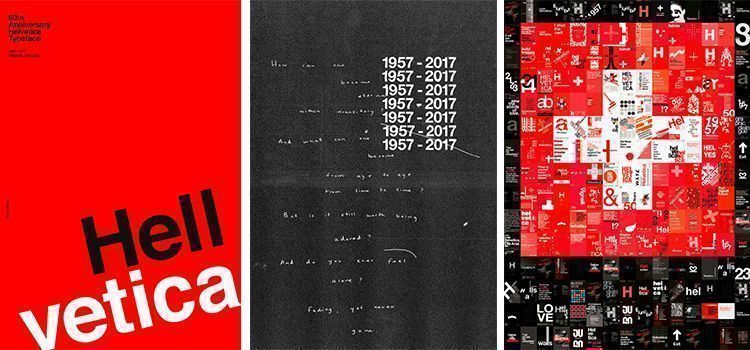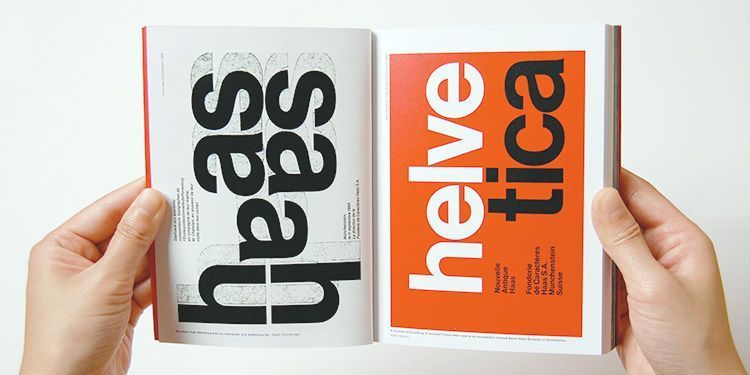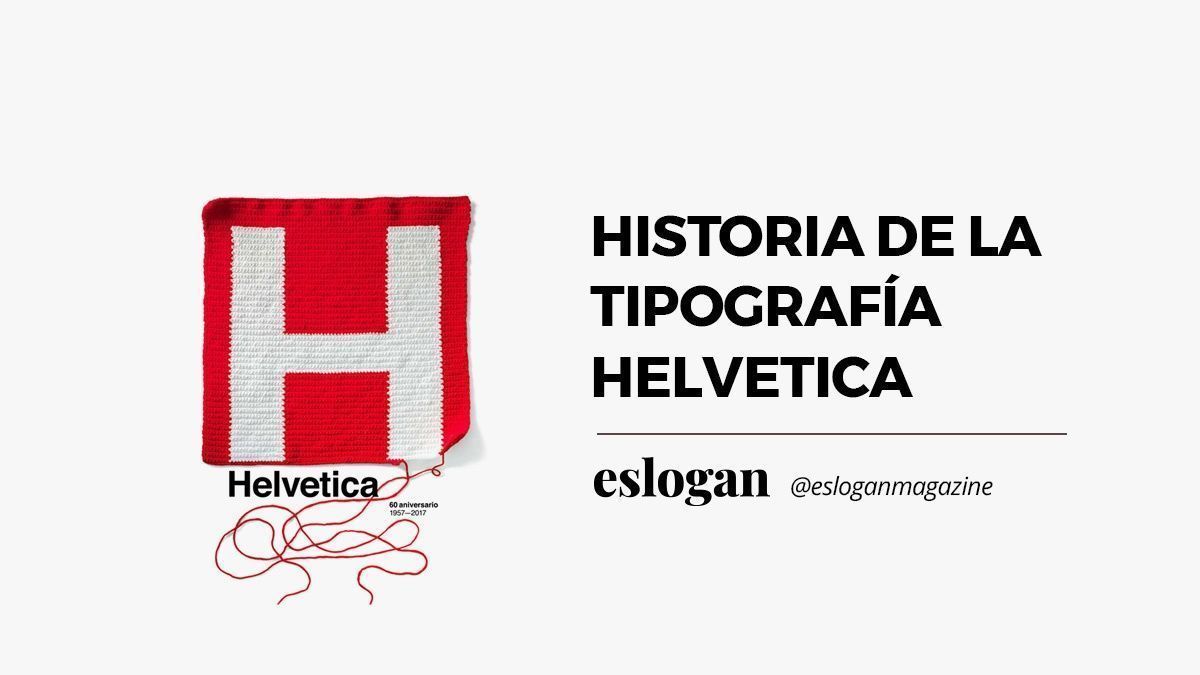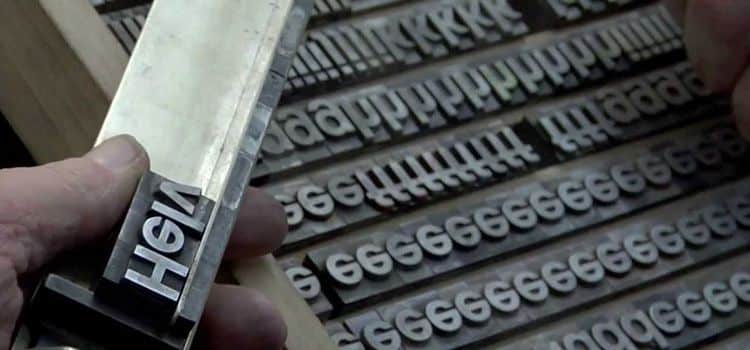
Historia de la tipografía Helvetica
Historia Tipografía Helvetica
La popular tipografía Helvetica cumple 60 años. Repasamos su historia, creación y aplicación.
La tipografía Helvetica cumple 60 años. La que podríamos definir como una de las tipografías legendarias, máxima expresión del estilo suizo que trajo la modernidad en el diseño a mediados del siglo XX y cuya influencia sigue vigente.
Hace ya 60 años que Max Miedinger y Edouard Hoffmann recibieron el encargo, por parte de la fundición suiza Haas’sche Schriftgießerei (Haas), de modernizar su tipografía sans serif. La tipografía Helvetica apareció en nuestras vidas para quedarse. Hoy, vamos a repasar la historia de la tipografía más celebrada.
Origen de la tipografía Helvetica
Historia Tipografía Helvetica
En 1957 Max Miedinger recibió un encargo de Edouard Hoffmann (Fundición Haas) para modernizar el estilo de la tipografia tipo sans-serif de la casa tipográfica. Esta tipografia era Haas Grotesk y se basaba en el Akzidenz Grotesk de la Fundición Berthold de finales del siglo XIX. Miedinger rediseñó la tipografía, convirtiéndola en la «Neue Haas Grotesk».
La tipografía conserva el nombre hasta 1961, año en que la Fundición Stempel adquirió la Fundición Haas. Los nuevos dueños (con Walter Cunz a la cabeza) decidieron desarrollar una serie completa con diferentes pesos, y renombrarla como «Helvetica».
La Fundición Stempel la lanzó comercialmente para las máquinas Linotype, y en poco tiempo, y gracias un boom de la exportación del diseño objetivo (más conocido como Estilo Tipográfico Internacional), la Helvética se posicionó entre las tipografías más usadas de la historia.
Características de la tipografía Helvetica
Características Tipografía Helvetica
La Helvetica es un tipografía eficaz para uso cotidiano, especialmente para titulares (poco menos para cuerpo de texto). Su éxito se debe a su estupenda escalabilidad en todo tipo de situaciones. También a su uso durante el período en que la corriente del estilo internacional marcó la pauta del grafismo.
De palo seco, redondeada, con una gran altura de la x y sin florituras. Favorece mucho su uso el hecho de contar con tantos pesos distintos, que la hacen adecuada en prácticamente cualquier contexto. Destacan la pierna de la “R” o el rabo de la “a”, así como la barbilla de la “G”. Podríamos decir que carece de modulación en sus trazos, más al compararla con una de sus rivales, la Univers.
La Helvetica tiene una preferencia por la fotografía en lugar de ilustraciones o dibujos. En ella predomina la información basada en la claridad, la legibilidad y la objetividad, usando esas tipografías sin serif que reflejaban el espíritu progresista de una época.
Aplicación de la tipografía Helvetica
Cuando vas caminando por la calle, te fijas en aquel rotulo que antes no habías visto. Observarás que su nombre está compuesto por una serie de letras que te resultan muy familiares, y no sabes por qué. Porque inconscientemente los tienes interiorizados, porque sin darte cuenta los has ido viendo en todo tu recorrido a diario. Muchos de esos elementos físicos y rutinarios están vestidos en la considerada como la más bella de entre todas las tipografías de todo el mundo: La Helvetica.
Logotipos Tipografía Helvetica
Aunque sus detractores comenten que a tamaños pequeños, “la tipografía se comporta de manera defectuosa, fragmentando ópticamente los ejes de lectura”. Varios grandes diseñadores han defendido la Helvética sólo para el uso en titulares y a gran tamaño (entre ellos Wolfgang Weingart y Paul Rand).
Apple introdujo en 1984 el primer ordenador personal con interfaz gráfica. Con ello se democratizó la accesibilidad a las herramientas de diseño. Y en 1986 Adobe lanzó una colección de tipografías que incluía la Helvetica Neue. Una revisión importante del trazado del tipo original, con una estructura más unificada de alturas y anchuras.
60 aniversario Tipografía Helvetica
Documental Helvetica